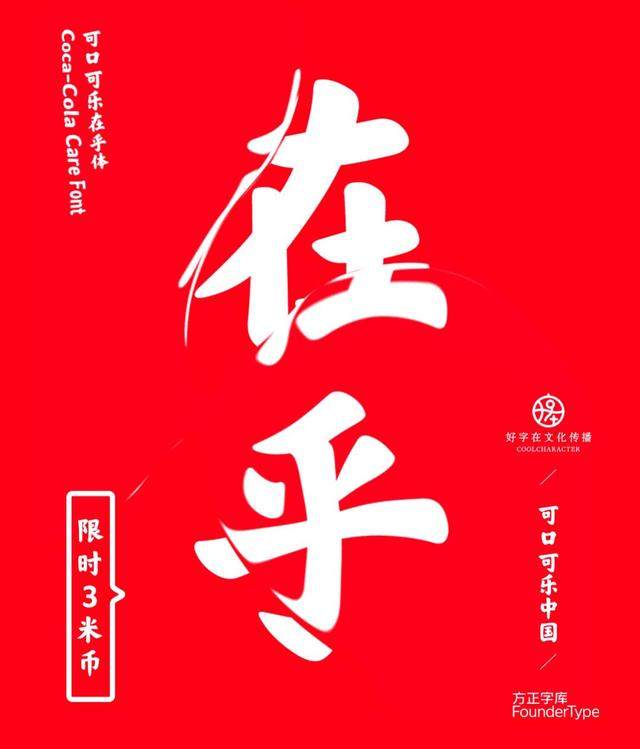
可口可乐公司在上周成立134周年的时间点,联合方正字库以及汉字推广机构好字在共同开发了一套全新的品牌定制字体,这套字体命名为“可口可乐在乎体”,历时一年多时间开发。在这套字体当中,“可口可乐”四个字的字形,完整还原了可口可乐重新回到中国市场时使用的经典商标字体。
据介绍,“在乎体”是根据GB2312字符集设计制作的,但特别收录了GBK字符集中“凊”“鹍”等汉字,使用在乎体可以打出《千字文》的全文。在乎体还包含了:特别设计制作的中华传统民俗文化中的“合体字”以及陕西特有的“biang”字,利用在乎体的Opentype特性,可以方便地调用这些特别设计的字符。
此外,可口可乐中国企业特别定制版字体中,还包含了主品牌标识:“在乎的笑脸”表情符号。来自于“在乎体”的中文笔画。
可口可乐在乎体字体包含了7745个字符(汉字6769个,其他字符976个),免费授权个人非商业使用、公益使用。至于被命名为“在乎体”的原因,根据可口可乐的解释,它所呈现的圆融、力量、担当、从容、进取,是对『在乎』这两个字的理解与诠释。